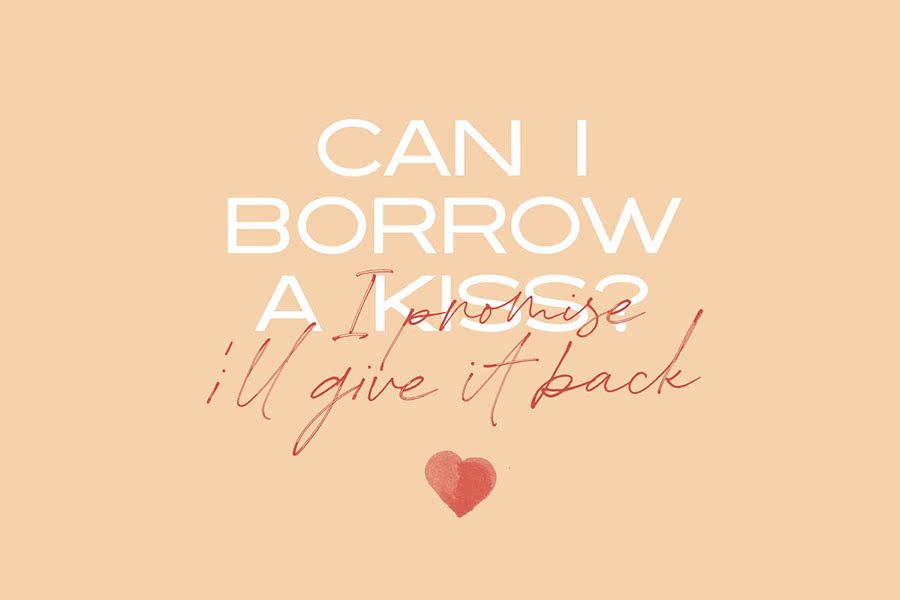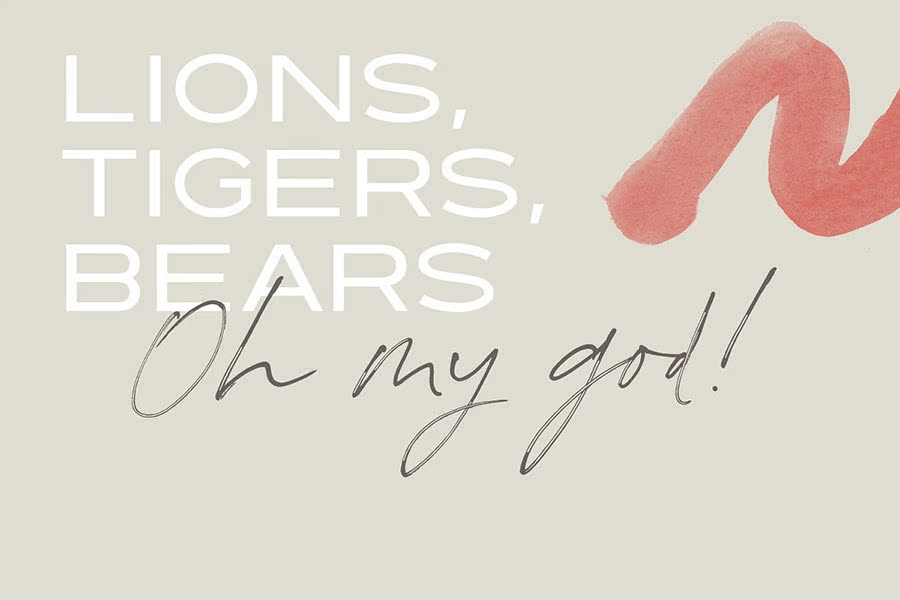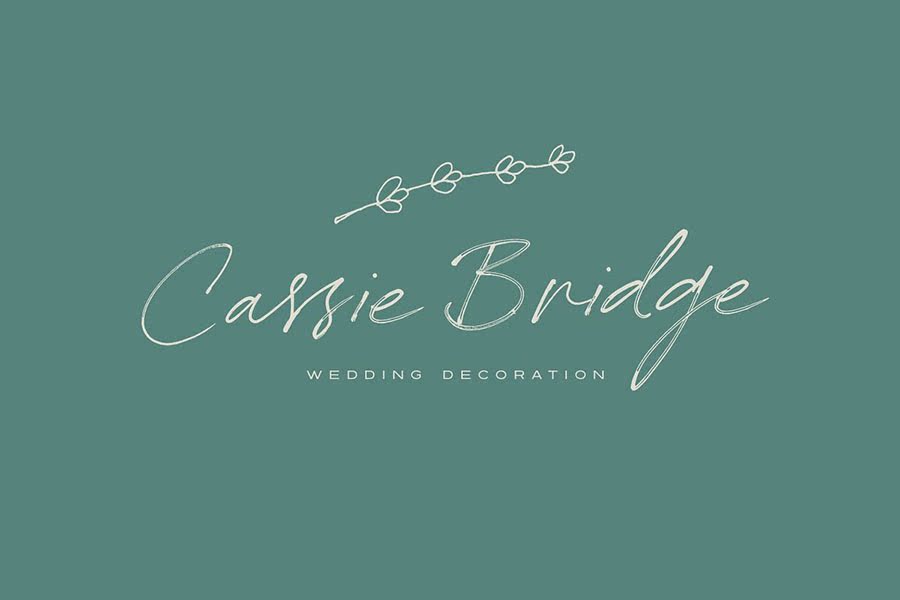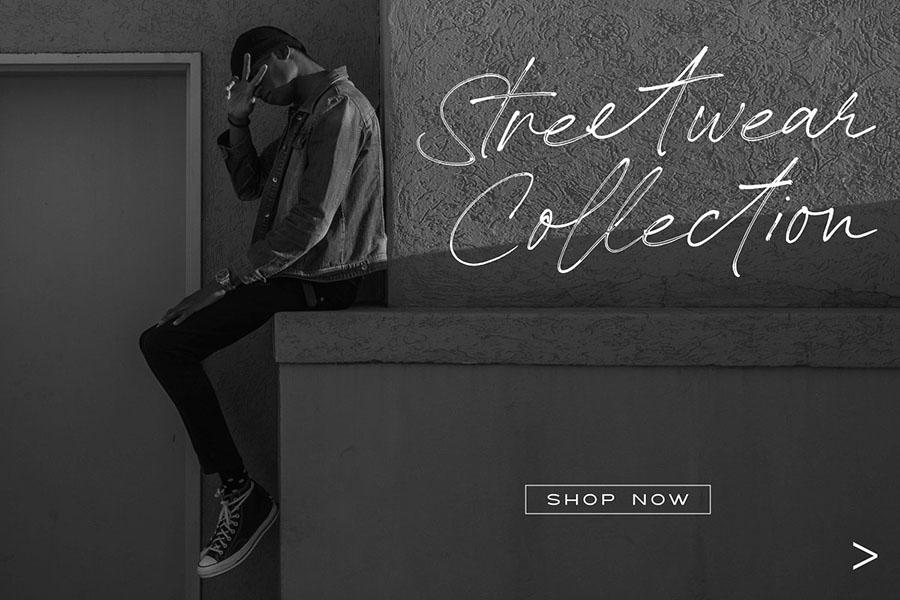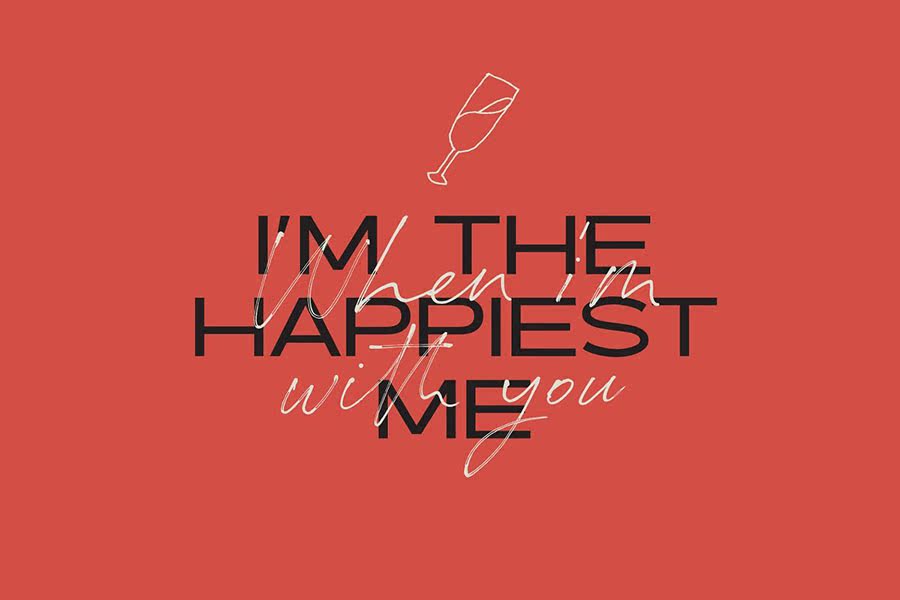
TheredstockHandwritenfontisher!想象一下Fontsasavisualcomestic。是的,从这个想法开始,我们带着被称为HeredStock的Tof Fonts和Designer来到这里。一个具有“几乎是空的”圆珠笔效果的真实手写字体Fonts。完美地适合您的徽标、品牌、每个项目的Ansysignature,任何东西。感受到永远的满足感,无论头部受到什么样的冲击,都会让您几乎看不到任何东西。